2023 年 30 种最佳儿童字体(免费和付费)
已发表: 2023-06-30您是一位平面设计师,正在努力寻找完美的儿童字体来增强您的项目设计吗? 别再犹豫了! 我们关于 30 种最佳儿童字体的博客文章已经为您介绍了。
在本文中,我们将探讨专为儿童项目设计的前 30 种字体。 您是否知道选择正确的字体可以显着影响孩子对内容的参与和理解? 根据威奇托州立大学心理学系进行的一项研究,形状不规则和字母高度不同的字体更容易让孩子阅读和理解。
事不宜迟,让我们深入了解我们精心挑选的市场上最好的儿童字体列表。 从俏皮、异想天开到大胆、精致,我们为每个人提供了适合的东西。
最佳高级儿童字体
如果您希望使用优质字体来提升您的设计,那么您来对地方了。 看看我们为儿童项目精心挑选的最佳优质字体,它们一定会为您的工作增添一丝精致和趣味。
童话
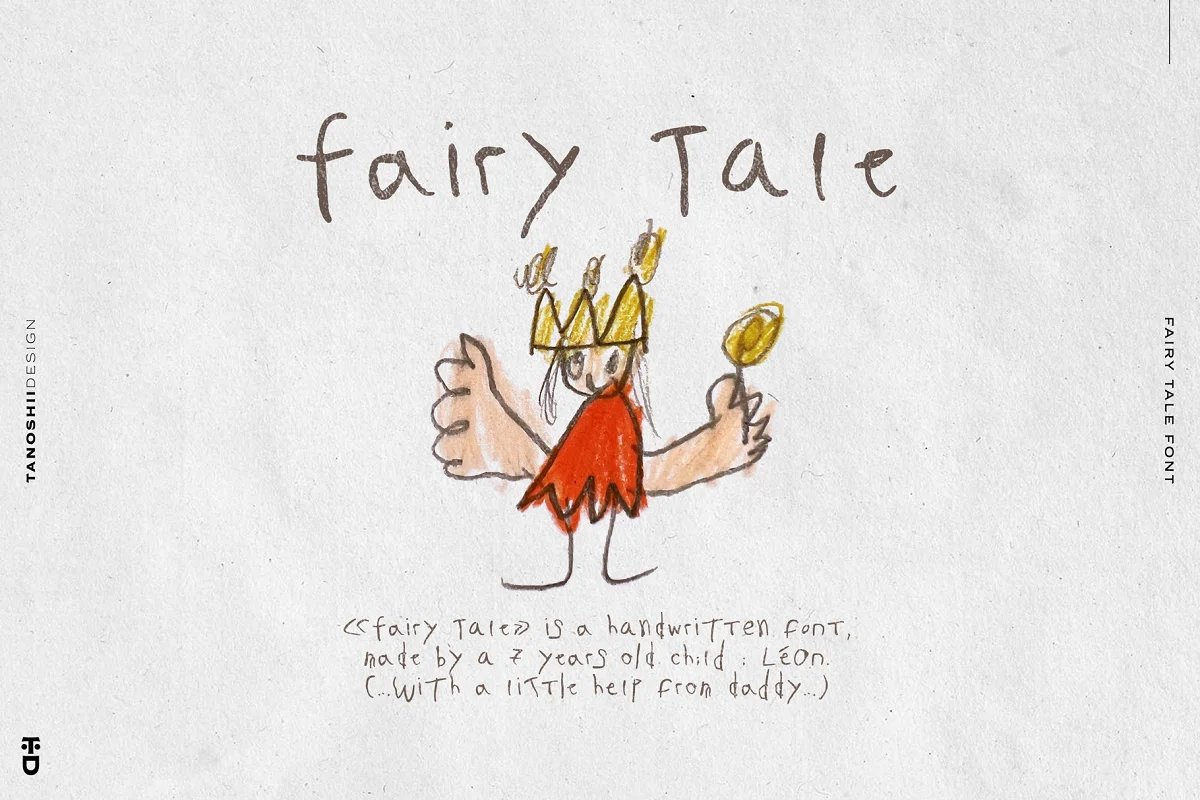
FAIRY TALE 是一款迷人的手写字体,由七岁儿童制作,使其成为儿童字体的完美选择。 这种可爱的字体是为小孩子设计的,将为任何项目带来奇思妙想和魔力。
可爱的孩子
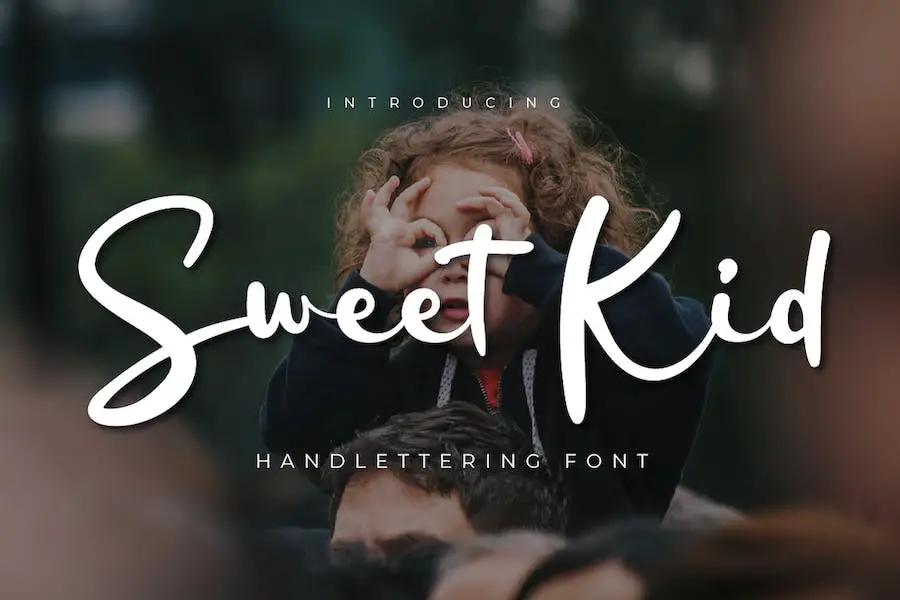
Sweet Kid 是一种优雅而精致的手写字体,非常适合希望为其项目增添一丝精致感的设计师。 这种字体圆润且独特的字母使其成为真正的杰作,具有令人难以置信的多功能风格,可用于各种设计。
如果您希望通过永恒而精致的外观来改进您的设计,那么 Sweet Kid 是完美的解决方案。 Google Kids Fonts 将因其独特而优雅的风格而得到增强,使其从其他设计中脱颖而出。
莱昂
LEON 是一种 OTF 儿童字体,捕捉了幼儿笔迹的精髓。 这种手写字体非常独特,可为您的设计增添个人风格。 其仅限 CAP 的功能使其从其他字体中脱颖而出,确保您的文本易于阅读。
此外,LEON 对于从事 Adobe Kids Fonts 设计的设计师来说是一个不错的选择。 使用这种字体可以让您的项目看起来更有趣、更有吸引力,使其成为设计以儿童为中心的材料(例如游戏、网站和教育材料)的理想选择。
勇气小子
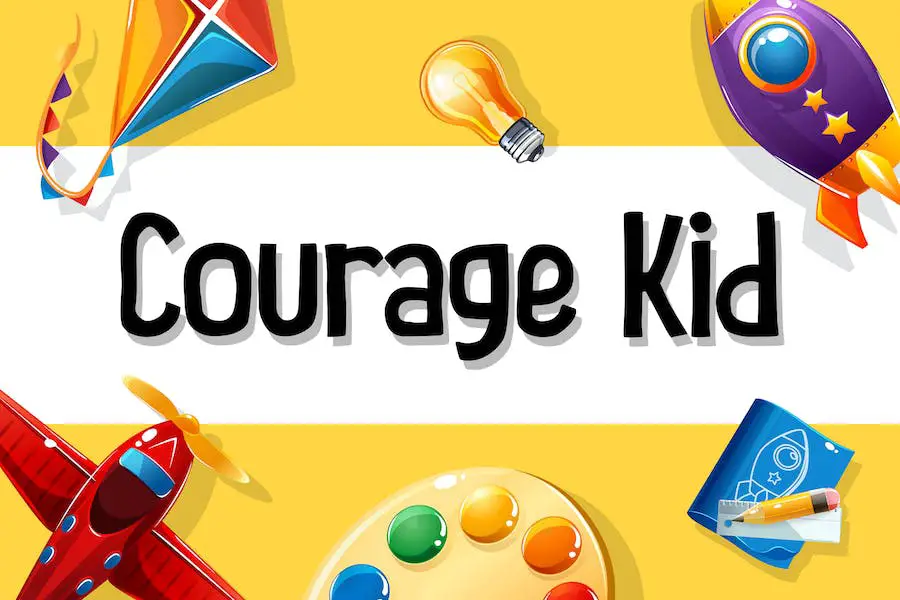
Courage Kid 是一种捕捉童年兴奋和好奇心本质的字体。 构成每个字母的不完美线条反映了我们探索周围世界所带来的不完美和成长。
该字体非常适合各种创意项目,例如儿童书籍、在线游戏、活动海报、学校用品、电影标题、YouTube 封面和社交媒体页面封面。 它采用 OTF/TTF/WOFF 格式,包括基本的拉丁语 AZ 和 az、数字和标点符号。
布皮
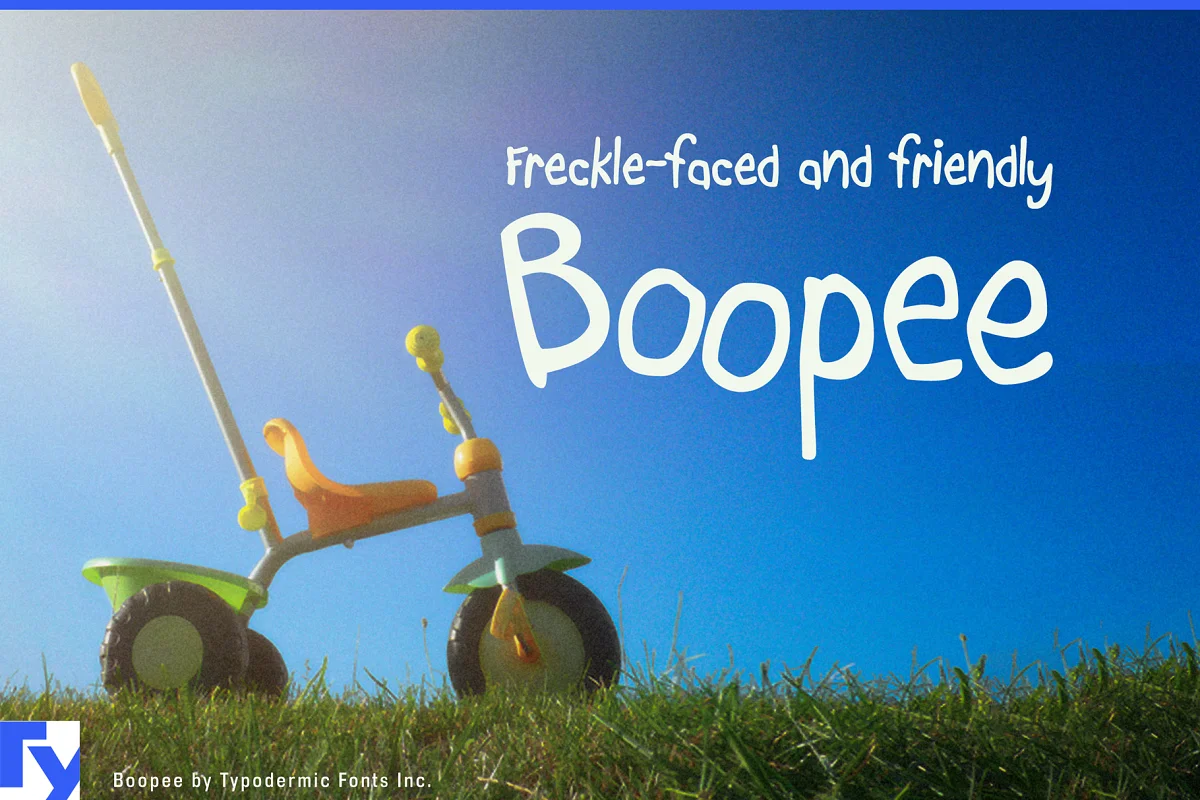
Boopee 是一种独特而有趣的字体,非常适合为您的设计增添一丝魅力。 尽管存在缺陷,但这种风度翩翩的字体易于阅读,使其成为各种设计应用的多功能选择。
作为 Word 中最好的儿童字体之一,Boopee 古怪的形状和不均匀的线条赋予它一种在其他字体中很难找到的人性化风格。 其凌乱但清晰的风格使其成为创建吸引受众注意力的海报、徽标和社交媒体图形的理想选择。
儿童乐园
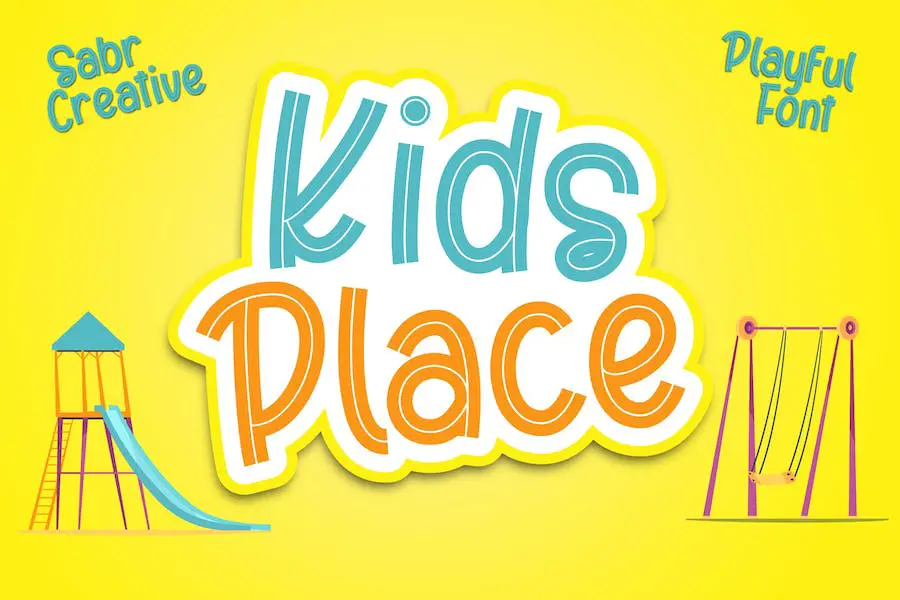
对于希望以俏皮、可爱和干净的风格改进其项目的平面设计师来说,Kids Place Font 是完美的补充。 该字体包括三种样式,可以轻松组合以满足您的特定项目需求。
如果您正在寻找在 Canva 上使用的字体,Kids Place Font 就是您的最佳选择。 它的多功能性和可读性使其成为任何项目的绝佳选择。
懒狗
因此,如果您正在市场上寻找 Circuit 的儿童字体,请务必查看 Lazydog,看看它如何激发您的下一次创意尝试!
儿童漫画
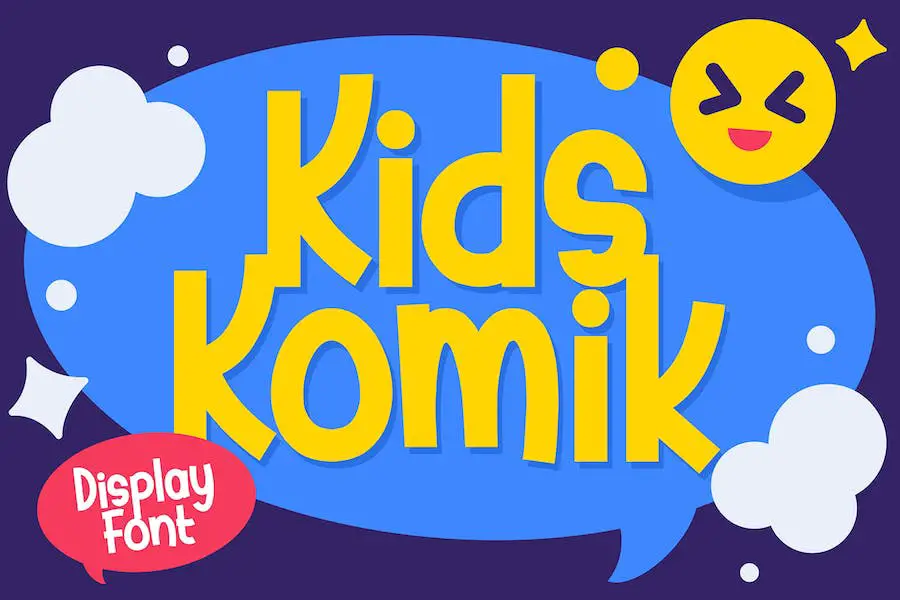
这种字体具有俏皮的漫画外观,非常适合针对儿童的设计。 凭借其欢快而充满活力的外观,它可以帮助您的设计更加生动有趣。 但不要让它可爱的外表欺骗了你; 这种字体也具有足够的通用性,可以在各种其他环境中使用。
游戏时间
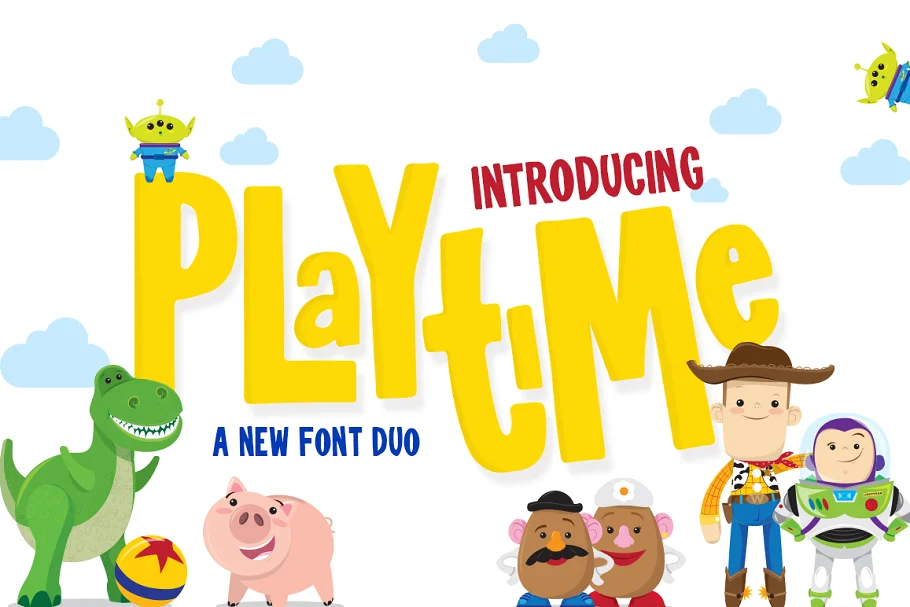
Playtime 是一种令人兴奋的新型字体,非常适合您的所有创意需求。 这种古怪而可爱的字体用途广泛,可以用于任何场合,使其成为世界各地设计师的必备字体。
该字体俏皮的字符一定会吸引每个人的注意力,您会喜欢将它们组合起来创造独特的外观是多么容易。
无论您是在寻找用于儿童读物的字体、有趣的网站设计,还是古怪的纹身,Playtime 都是完美的选择。 其可爱又大胆的风格一定会彰显个性,并给看到它的人留下持久的印象。
微笑孩子
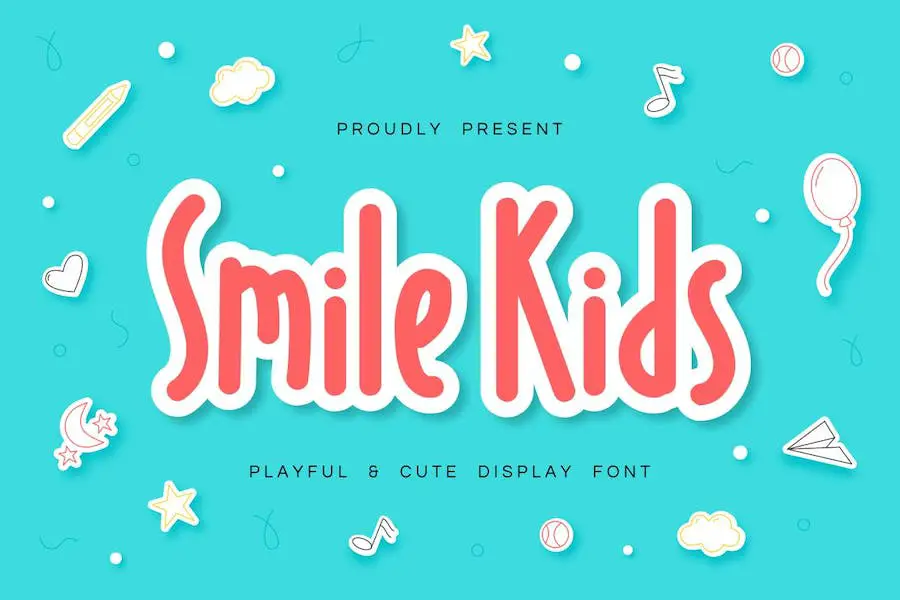
Smile Kids 是一种有趣且有吸引力的显示字体,可用于增强各种儿童项目的设计。 该字体带有大小写字母、数字、标点符号和多语言支持,使其用途广泛,适合多种用途。
Smile Kids 能够在所有大写或句子大小写下同样出色地工作,为设计师提供了灵活性。 该字体的多功能性和迷人的风格使其成为那些为儿童项目寻找儿童字体的人的绝佳选择。
梅托里乌斯
Metorius 是市场上可以找到的最好的商业用途儿童字体之一。 这种字体具有出色的俏皮外观,非常适合应用于儿童故事书或任何其他正式形式,如邀请函、徽标、贺卡、小说、杂志、包装、化妆品、时尚等。
综上所述,Metorius是一款可以用于商业用途的顶级儿童字体。 其有趣俏皮的外观非常适合儿童故事书,但也非常适合许多其他类型的项目。
凭借其多语言支持、连字和 PUA 编码,您可以创建独特的设计来吸引观众的注意力。
雨云
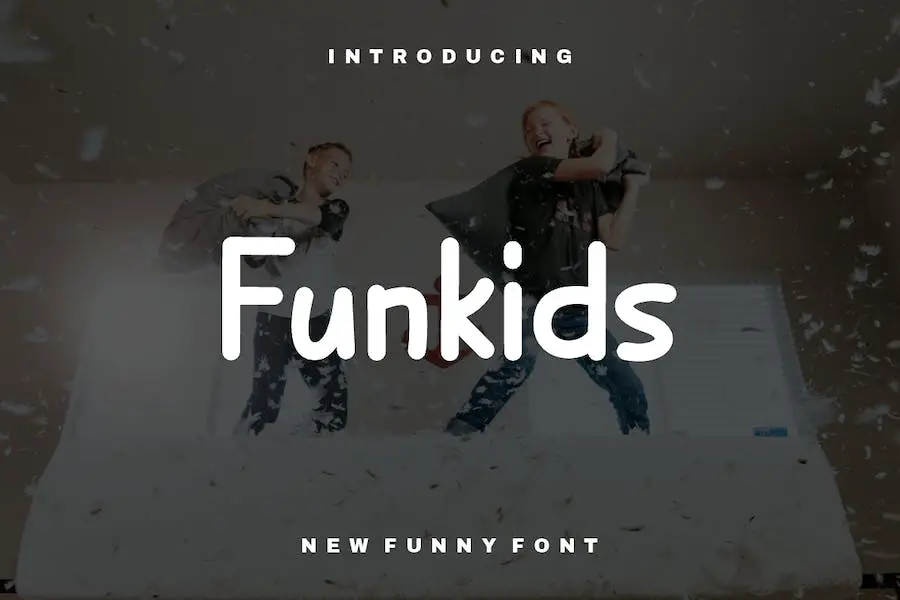
Nimbus 字体是一种承诺为任何设计项目增添一丝俏皮感和现代感的字体。 凭借其简洁的线条和简单而优雅的风格,这种字体非常适合任何想要创造引人注目的设计并脱颖而出的人。
Nimbus 字体的突出特点之一是它的多功能性。 无论您是创建徽标、设计网站还是从事印刷项目,这种字体都可以轻松集成到您的设计中,而不会感觉不合适。
此外,由于其现代而有趣的外观,这种字体非常适合针对年轻受众的项目。
恐龙小孩
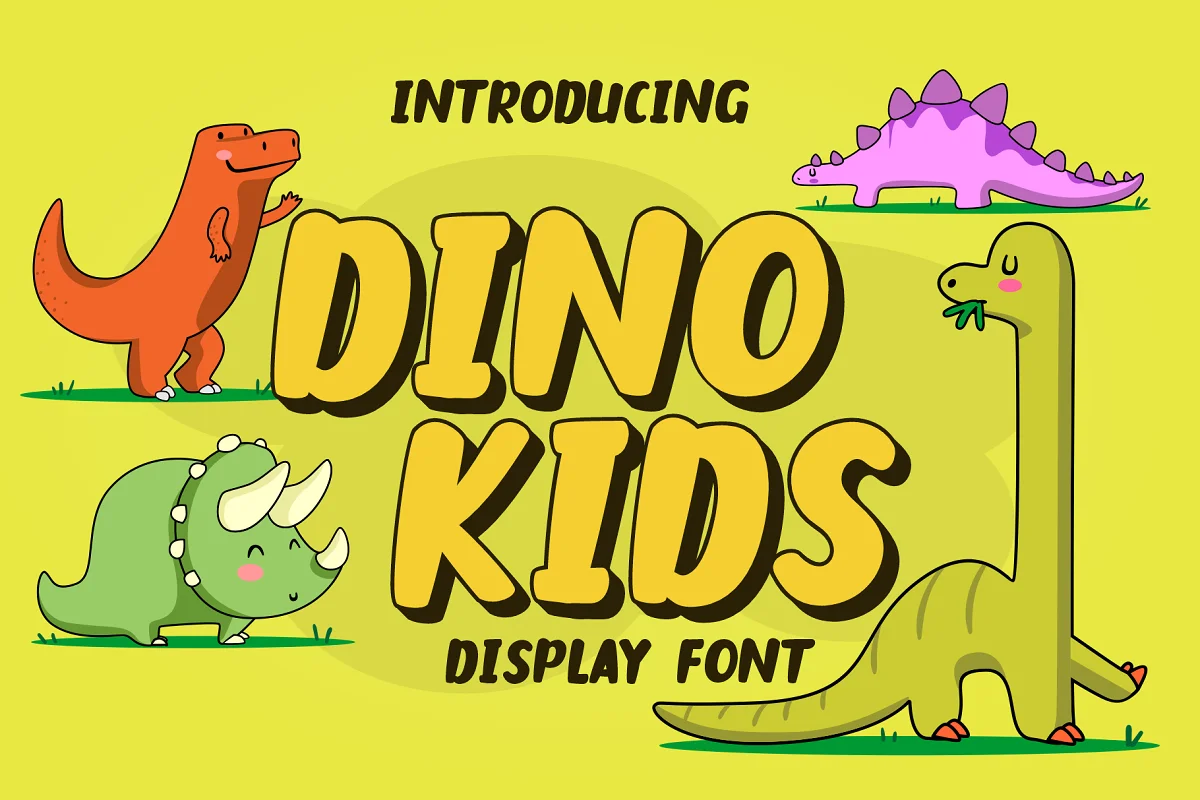
Dino Kids 是一款受俏皮和手写字体风格启发的字体,旨在为您的文本增添美感。 这些字母经过精心制作,可为您的项目带来独特的触感。 该字体有两种文件类型:otf 和 ttf,以及多语言支持。
Dino Kids 与其他字体的区别之一是它的 PUA 编码,它允许从大多数设计软件的字符映射表中访问额外内容。 此外,该字体还包括一个挤压版本,以增加尺寸和深度。
懒孩子
Lazy Kids 是一款新的俏皮儿童字体,具有自然的感觉和可爱的触感。 该字体是手工制作的,可为您的设计带来美丽、自然的外观和复杂的细节。
它非常适合任何设计项目,如邀请函、徽标、书籍封面、工艺品或您能想到的任何其他设计目的。 这种字体是 PUA 编码的,这意味着您可以访问所有神奇的字形和特殊功能,包括连字字形。
丛林人物
Jungle Character 是一款迷人的字体,具有 52 个手绘字符,非常适合任何需要俏皮和异想天开的风格的设计项目。 每个角色都经过独特制作,为着色或留空提供了无限的可能性。
总体而言,对于任何想要通过年轻魅力来提升设计的设计师来说,丛林角色都是一个极好的补充。
金戈儿童
Gingo Kids 有四种不同的款式:常规、薄型、常规粗糙型和薄型粗糙型。 Gingo Kids 包含从 A 到 Z 的所有字符以及数字和标点符号,拥有创建有趣且独特的设计所需的一切。
该字体可在 PC 和 Mac 上无缝运行,并且安装非常简单。 另外,它经过 PUA 编码,可为您的项目提供更多多功能性。
木户
Kido 字体是一种令人兴奋且有趣的显示字体,非常适合任何儿童主题的设计项目。 它配备 OTF/TTF/WOFF 字体,可在 PC 和 Mac 上使用。
Kido 拥有大量的字形和连字,为品牌项目、徽标设计、社交媒体帖子、书籍封面、产品包装、标签、邀请函和文具提供了独特而有趣的触感。
总之,Kido 是任何设计师工具包的绝佳补充,它为传统显示字体提供了有趣且富有想象力的旋转。
它的多功能性使其成为任何与儿童或有趣主题相关的项目的绝佳选择。 那么,为什么不尝试一下 Kido,看看它如何提升您的下一个设计项目呢?
最好的孩子
Best Kids 是一种迷人而古怪的显示字体,可为任何设计项目增添令人愉悦的感觉。 凭借其俏皮的外观,这种字体非常适合为儿童或那些想要为自己的作品增添一丝奇思妙想的人创建设计。
Best Kids 的突出特点之一是其独特的角色设计。 每个字母都有自己的个性,可以轻松创建引人注目且独特的设计。 此外,字体的粗线条和曲线使其高度清晰,确保您的信息清晰易读。
粗略的故事
Sketchy Story 是一种字体,非常适合那些希望为自己的设计项目增添一点乐趣和个性的人。 凭借其粗糙的边缘和手绘的感觉,这种瘦字体有两个版本:轮廓和填充。 两者可以一起使用,也可以单独使用,以创造出多种效果。
Sketchy Story 最好的事情之一就是它的多功能性。 其俏皮的性质使其成为苗圃印刷品和儿童书籍的理想选择,但它也可以完美地作为更复杂设计的一部分。
该字体的粗糙边缘赋予其一种真实感和个性感,而这些是更精美的字体所缺乏的。
儿童故事
KIDS STORY 是一款令人惊叹的展示漫画字体字体,它将提升您的设计并使其脱颖而出。 凭借其迷人而俏皮的外观,该字体非常适合各种项目,包括书籍封面、品牌材料、徽标、T 恤、海报、婴儿时尚产品、漫画、引言等。
该字体附带您需要的所有标准字符,以及小写和大写字母、数字、标点符号、连字和国际字形。 您将收到 OTF、TTF 和 WEBFONT 文件,使其易于在各种平台上使用。
最好的免费儿童字体
正在寻找在孩子的项目设计中使用的最佳免费字体? 查看此精选列表,它们将为任何项目增添创造力和个性。 请务必继续阅读我们为儿童精选的 30 种令人惊叹的字体。
儿童
对于年龄较大的孩子,您可以尝试更复杂的字体和设计。 总的来说,您选择的字体应该与您的项目的基调和风格相匹配,并且易于阅读并吸引目标受众。
结论
总之,我们探索了儿童字体的世界以及它们如何改进您的项目设计。 通过使用这些适合儿童的字体,您可以为您的作品添加俏皮和有趣的元素,使其对儿童和成人都更具吸引力。